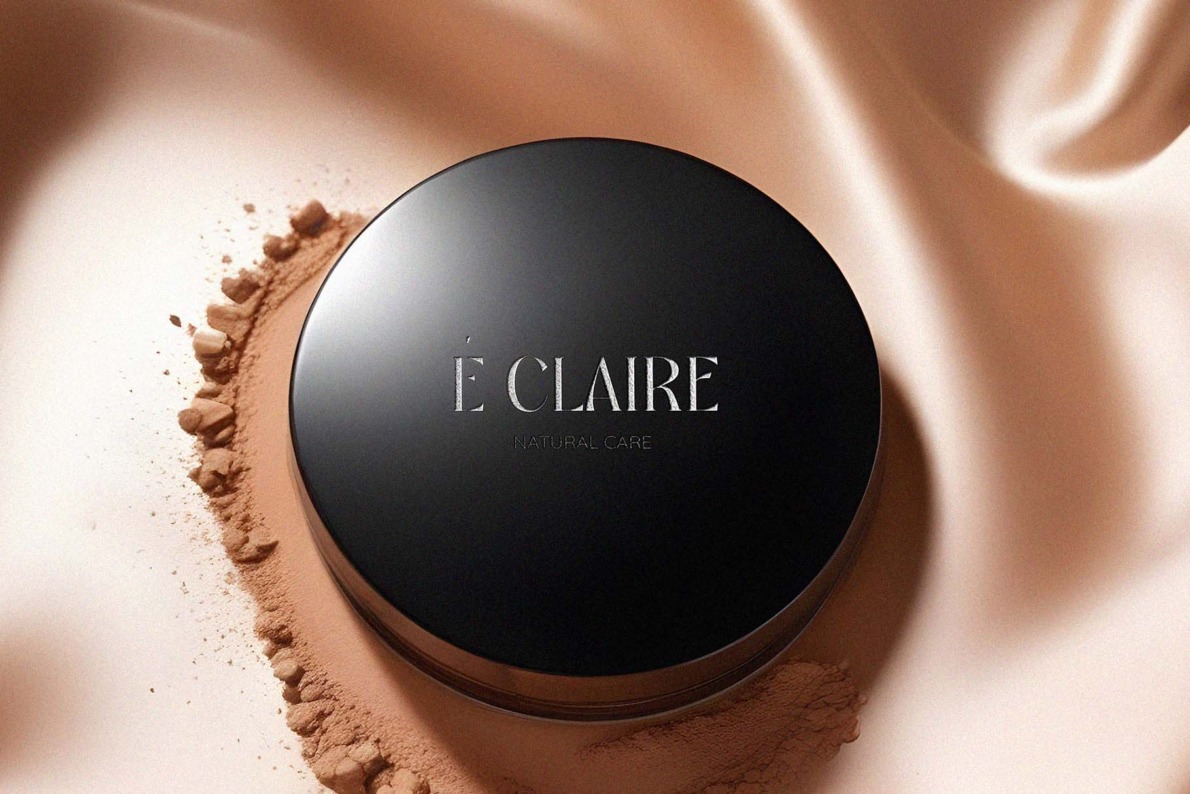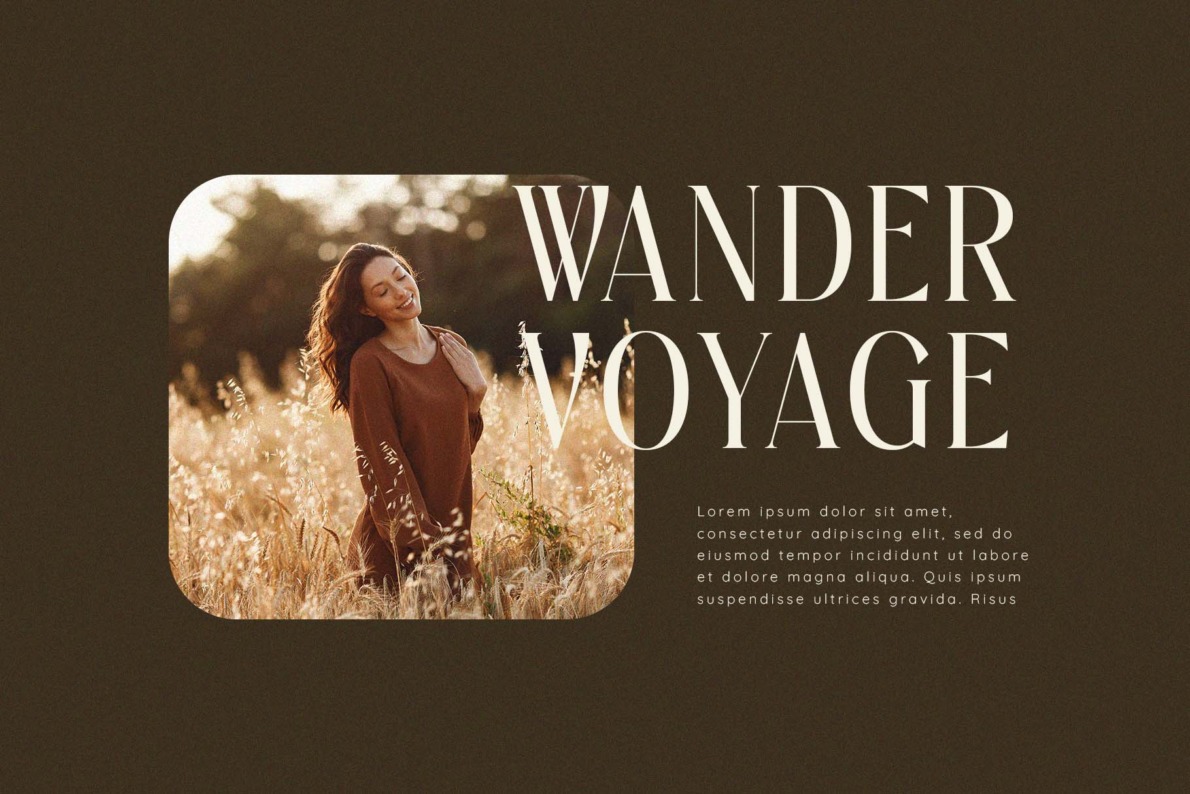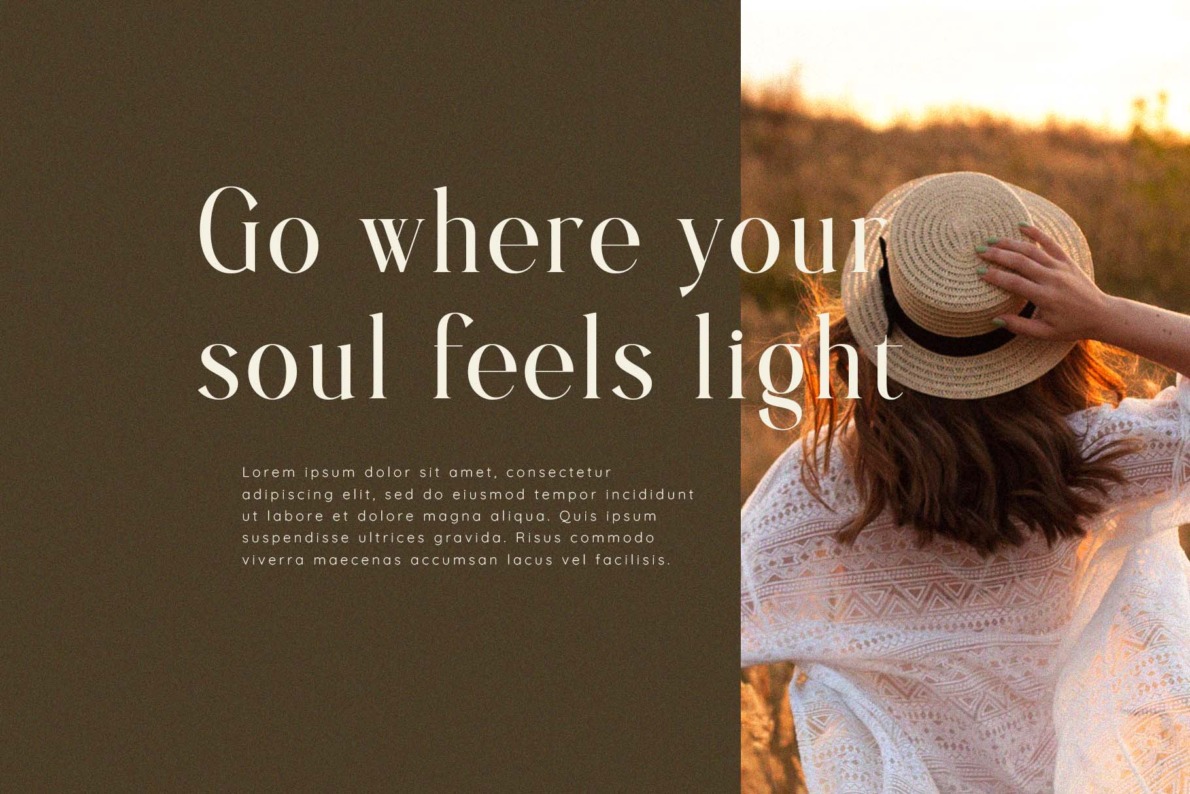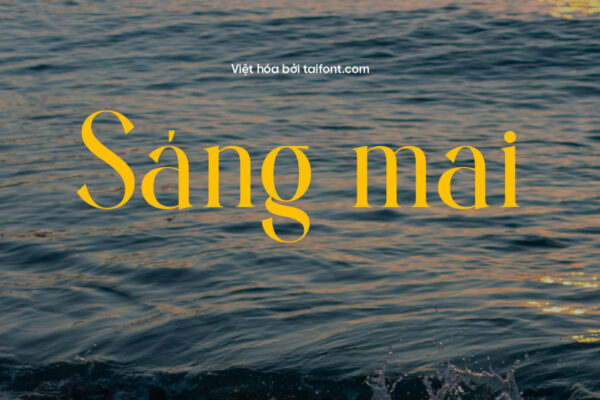
Giới thiệu về Font TF Regie Việt hóa
TF Regie Việt hóa là một font chữ có chân (serif) nổi bật với vẻ đẹp sang trọng, tinh tế và đầy cuốn hút. Font này được thiết kế với những đường nét được chăm chút tỉ mỉ, toát lên sự quý phái và thanh lịch, gợi cảm giác về sự hoàn hảo trong từng chi tiết. Regie là lựa chọn lý tưởng để tạo nên phong thái đẳng cấp và sự độc đáo cho mọi thiết kế.
Với sự tinh xảo trong từng ký tự và tính thẩm mỹ vượt trội, Regie là lựa chọn hoàn hảo cho các ấn phẩm cần sự sang trọng và khác biệt, đặc biệt là trong các lĩnh vực:
- Thiết kế thời trang: Hoàn hảo cho các thương hiệu thời trang cao cấp, từ logo, nhãn mác sản phẩm, lookbook, đến các chiến dịch quảng bá bộ sưu tập. Font này giúp truyền tải vẻ đẹp thanh lịch, đẳng cấp và độc đáo của trang phục, nâng tầm giá trị thương hiệu.
- Thiết kế mỹ phẩm: Lý tưởng để sử dụng trên bao bì sản phẩm, nhãn mác, catalogue, hoặc các chiến dịch marketing của các thương hiệu mỹ phẩm cao cấp. Regie giúp khẳng định chất lượng, sự sang trọng và vẻ đẹp tinh túy của sản phẩm, thu hút ánh nhìn của khách hàng và truyền tải thông điệp về sự quyến rũ, đẳng cấp.
- Branding (Nhận diện thương hiệu): Phù hợp cho logo, tagline hoặc bộ nhận diện thương hiệu muốn truyền tải sự đẳng cấp, uy tín và sự tinh tế. Regie giúp xây dựng một hình ảnh thương hiệu mạnh mẽ, dễ nhớ và có giá trị vượt thời gian.
- Thiết kế tạp chí và ấn phẩm cao cấp: Thích hợp cho các tiêu đề chính, lời dẫn hoặc nội dung bài viết trong các tạp chí về thời trang, làm đẹp, hoặc phong cách sống. Font này sẽ làm cho nội dung trở nên sống động, gần gũi và thu hút độc giả.
Với TF Regie Việt hóa, bạn có thể dễ dàng thổi hồn tinh tế, sang trọng và vẻ đẹp hoàn hảo vào các thiết kế, tạo ra những sản phẩm không chỉ đẹp mắt mà còn đầy cảm xúc và sức hút đặc biệt.